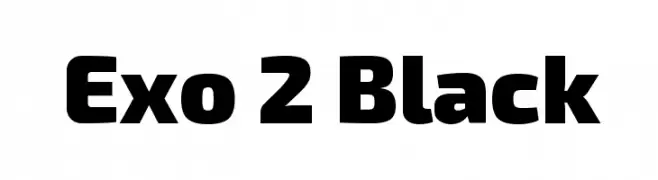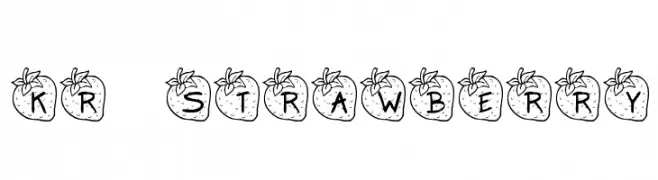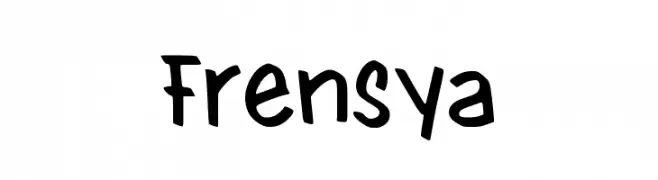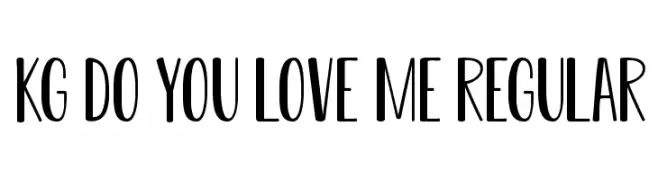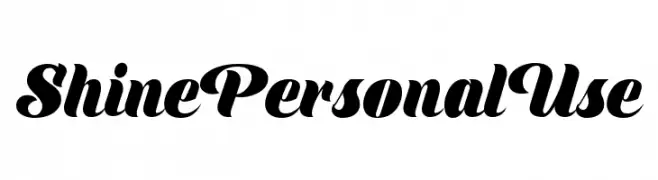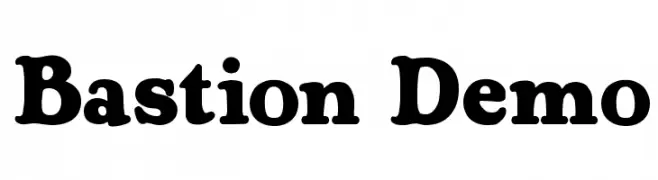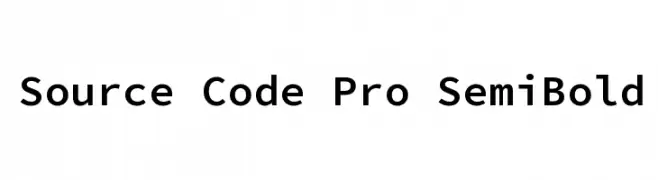
Добро пожаловать в раздел Топ шрифтов — здесь популярность встречается с качеством. Это самые скачиваемые и используемые шрифты нашего сообщества за этот год. Если нужны надежные варианты для логотипов, сайтов или соцсетей — начните отсюда.
Каждый топ‑шрифт отличается балансом, читабельностью и универсальностью. Здесь есть современные гротески, изящные скрипты, винтажные антиквы и минималистичные дисплейные семейства. Если не знаете, с чего начать, раздел «Топ» — ваш короткий путь к проверенной типографике.
A bold, modern font with a strong geometric structure and high legibility.
A lively cursive font with smooth, flowing strokes and a playful, elegant style.
A bold, decorative font with whimsical, artistic designs and intricate patterns.
A playful, handwritten-style font with a casual and friendly vibe.
A playful, hand-drawn font with tall, narrow characters and a whimsical style.
A bold, flowing script font with a modern and elegant style.
A dramatic, gothic-style font with sharp, jagged edges and a distressed look.
A clean, modern monospaced font with medium contrast and excellent readability.
Какие шрифты в топе прямо сейчас?
Дизайнеры любят Exo 2 Black, Cedarville Cursive, Slumgullion Plain, KR Strawberry and Frensya за чистые формы и широкий спектр применения — от фирменного стиля до лендингов и постеров.
Какие шрифты чаще всего выбирают для логотипов?
Геометрические гротески (наподобие Poppins, семейств стиля Gotham) — частый выбор для чистого, масштабируемого брендинга. Для более дружелюбного тона остаются актуальны скриптовые и рукописные шрифты. Сочетайте выразительный заголовочный шрифт с нейтральным текстовым для баланса и узнаваемости.